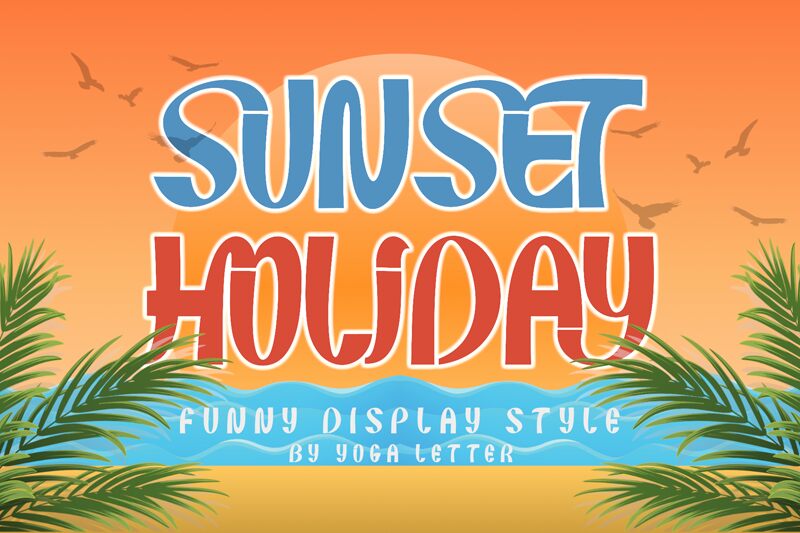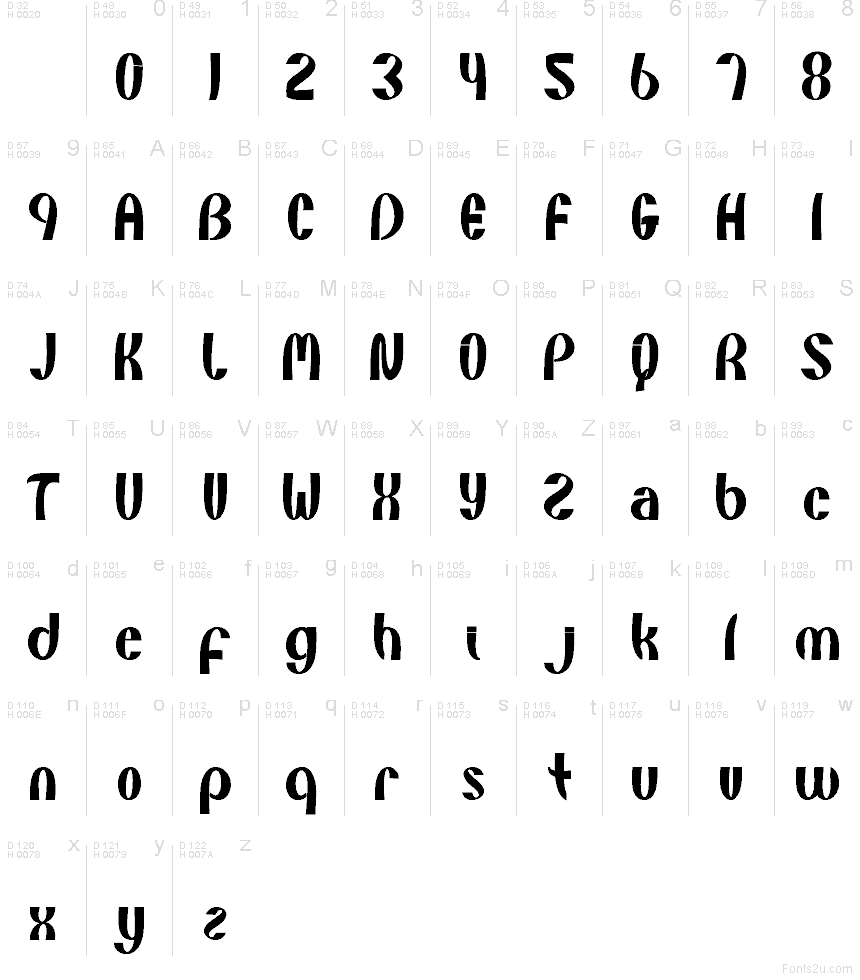
Sunset Holiday
Sunset Holiday de Yoga Letter es una fuente display gratuita con formas altas, estrechas y un ritmo elegante de alto contraste. Sus letras combinan curvas suaves con verticales firmes, y el S largo y envolvente le da a la familia su toque más distintivo.
Sunset Holiday funciona de maravilla en títulos de revistas, tarjetas festivas, carteles, invitaciones, etiquetas de productos e ideas de logotipos que requieran una estética serif refinada. Esta fuente gratuita aporta carácter a frases cortas, branding de eventos y packaging decorativo, manteniendo siempre una estructura ordenada y legible.